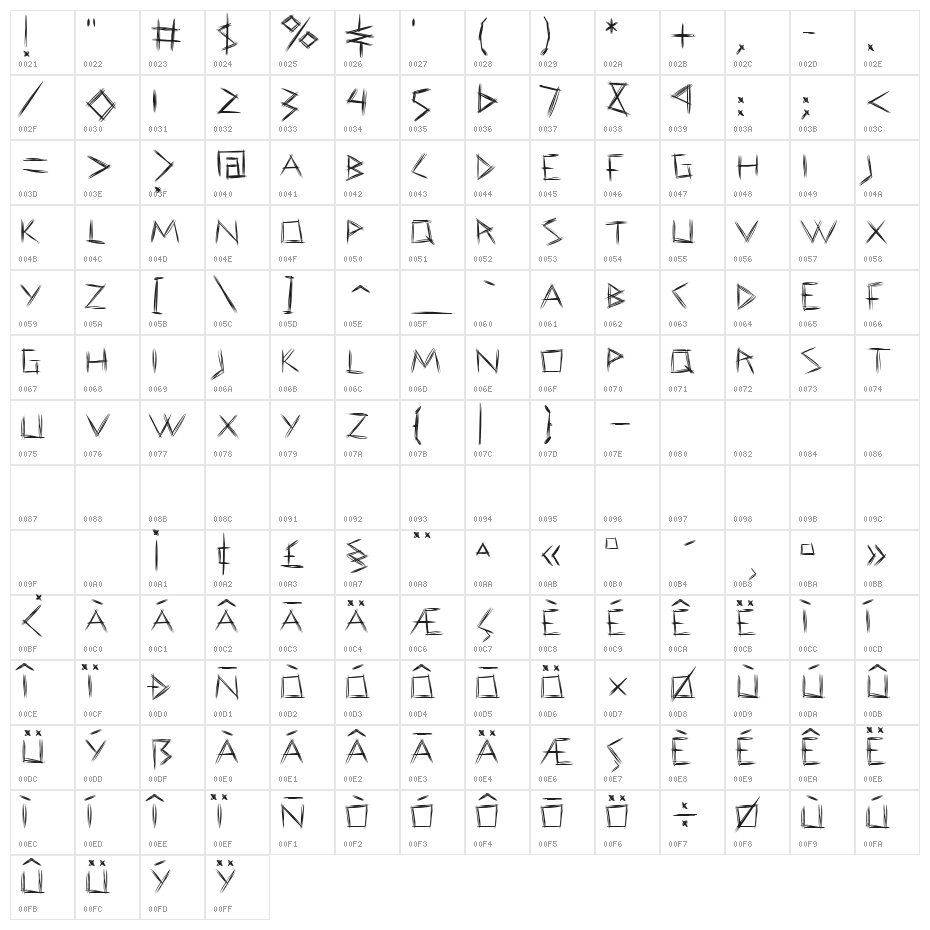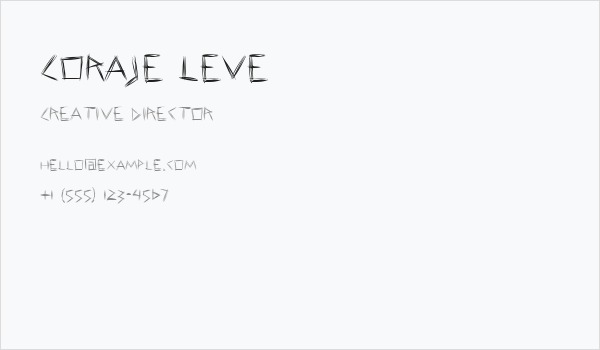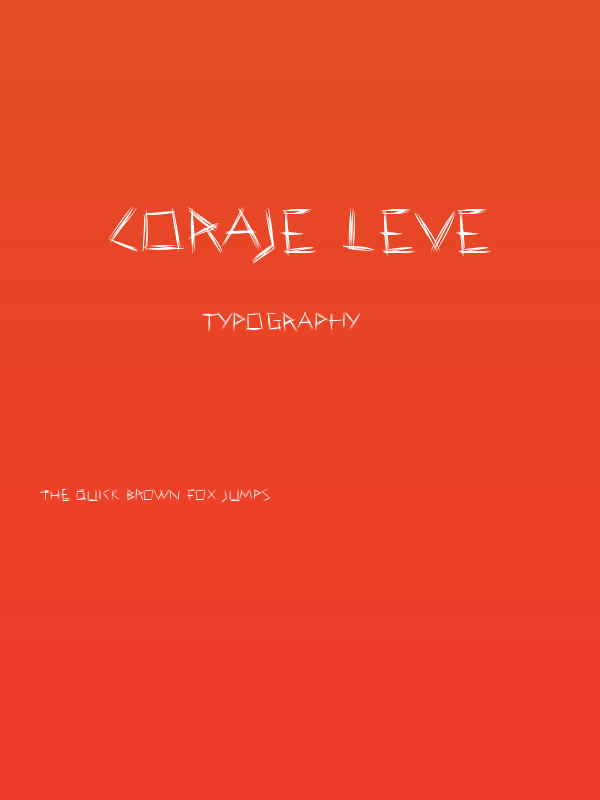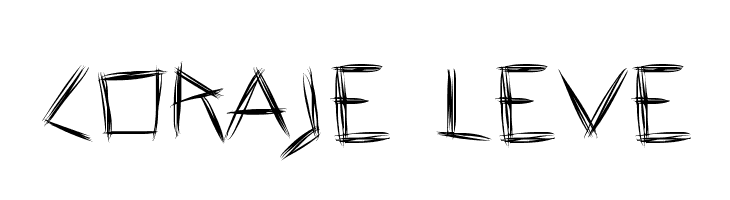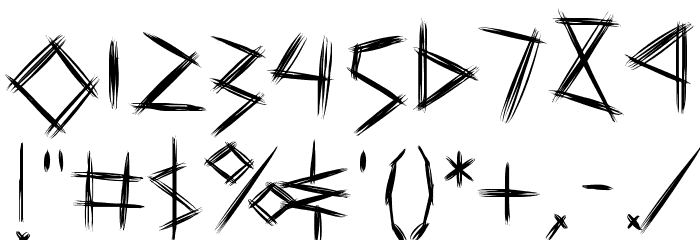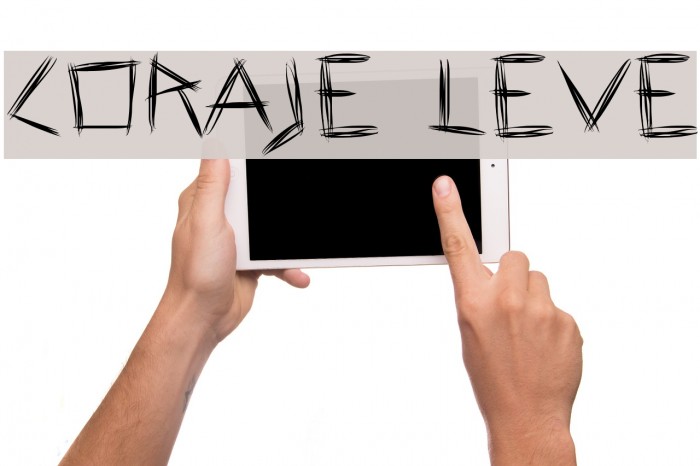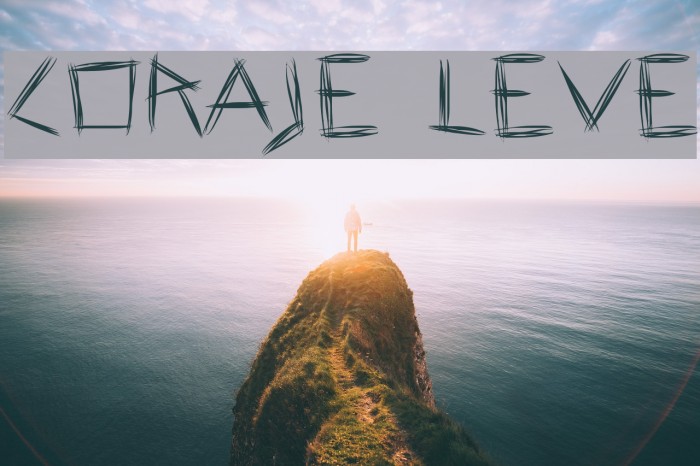
Coraje Leve Font
✎ Messy
| Gesamtstil | Modern, Edgy |
| Vorgeschlagene Projekte | Perfect for album covers, posters, streetwear branding, and any creative project that requires a bold, rebellious touch. |